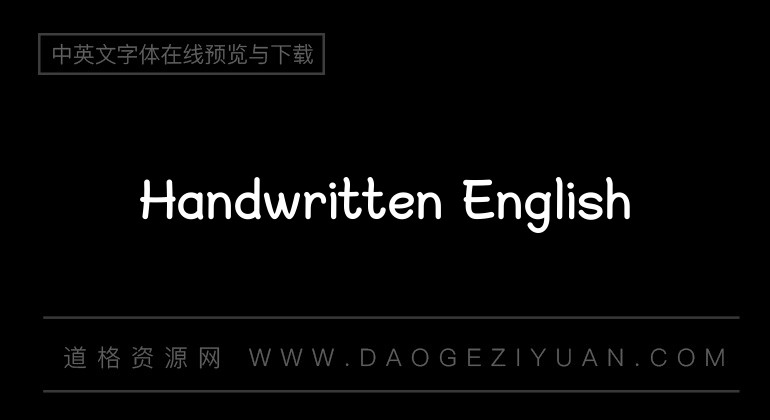
Handwritten English
Handwritten English字体是一种仿手写的字体风格,它的特点是像手写文字一样,具有一定的不规则性和个性化。这种字体常常被用于卡片、信件、海报、广告等场合,以给读者带来一种亲切、温暖的感觉。与传统的印刷体相比,Handwritten English字体更加自然、生动,也更加接近人们的日常写作习惯。因此,它最适合用于表现人情味、亲密感或个性化的文本内容。同时,由于Handwritten English字体的独特性,它也常常被用于设计师的创意作品,以突出他们的个人风格和创意思维。总之,Handwritten English字体是一种具有独特魅力的字体风格,能够为文本内容增添更多的个性化和温情。
Handwritten English是一款非常不错的手写艺术字体,具有很好的视觉感,适合于文化类的宣传设计、商业类品牌的广告和产品包装设计以及个性化文字排版等较多场景。